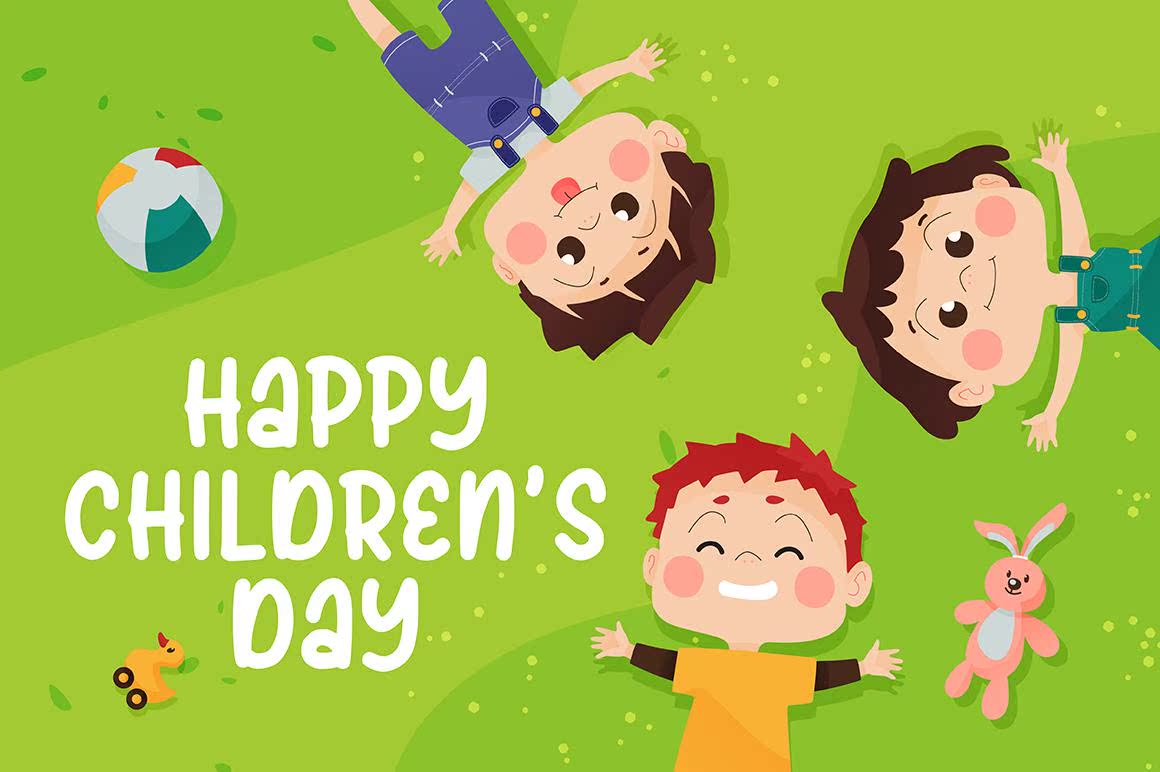
Brickhand、Sacute和Undisplay字体。这是一种令人愉快的风格,将您的项目提升到最高水平。以孩子般的游戏性获得创造性,并将其用于正确的儿童和学校项目!Brickhand、Sacute和Undisplay字体。这是一种令人愉快的风格,将您的项目提升到最高水平。以孩子般的游戏性获得创造性,并将其用于正确的儿童和学校项目!